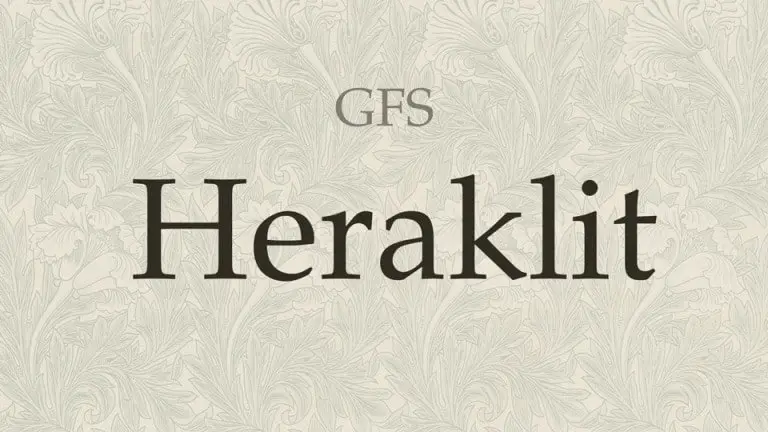
A GFS Heraklit Serif Font é uma escolha inteligente para quem busca harmonia entre a antiguidade e as características modernas do tipo grego. Criada pelo designer Hermann Zapf em 1953-1954, essa fonte serif traz um tom de elegância reminiscente das tipografias renascentistas como Palatino, Garamond e Aldus. É uma referência direta ao original projetado por Zapf, que foi desenvolvido antes da Segunda Guerra Mundial para publicações gregas. No final do século 20, esta fonte serviu de base para os caracteres gregos no Palatino Unicode. O projeto foi continuado quando George D. Matthiopoulos digitou originalmente os caracteres e Daniel Benjamin Miller e Antonis Tsolomitis criaram o GFS Heraklit-Regular. Através desses esforços, uma fonte de alta qualidade que combina elementos do passado e do presente surge para facilitar a tipografia moderna. GFS Heraklit Serif é uma escolha perfeita para projetos que buscam um equilíbrio entre história e simplicidade. Suas linhas suaves e detalhes meticulosamente criados o tornam uma opção versátil tanto para textos legíveis quanto para design gráfico sofisticado. É ideal para quem busca trazer uma aura de elegância ao seu layout, mantendo a tradição do tipo serif em um contexto moderno.